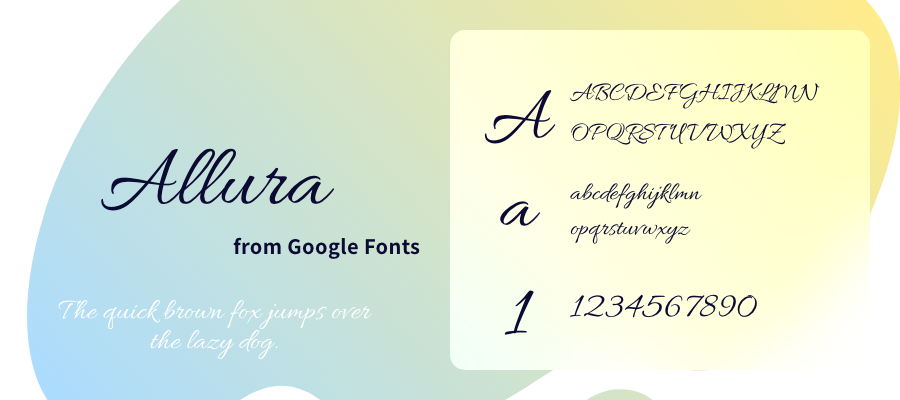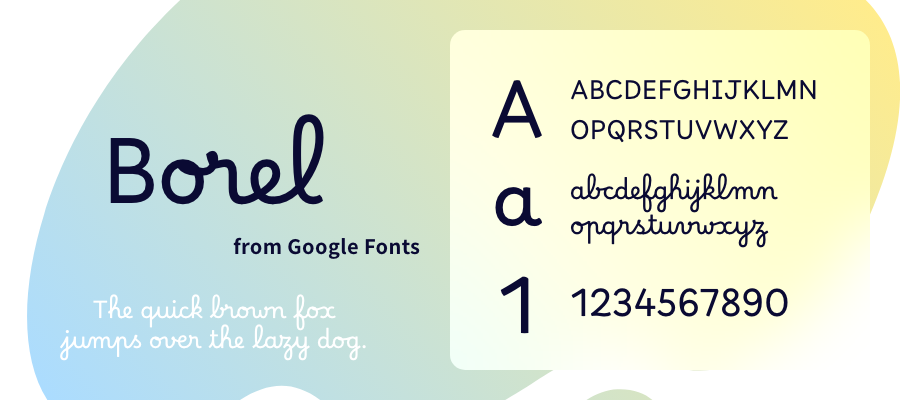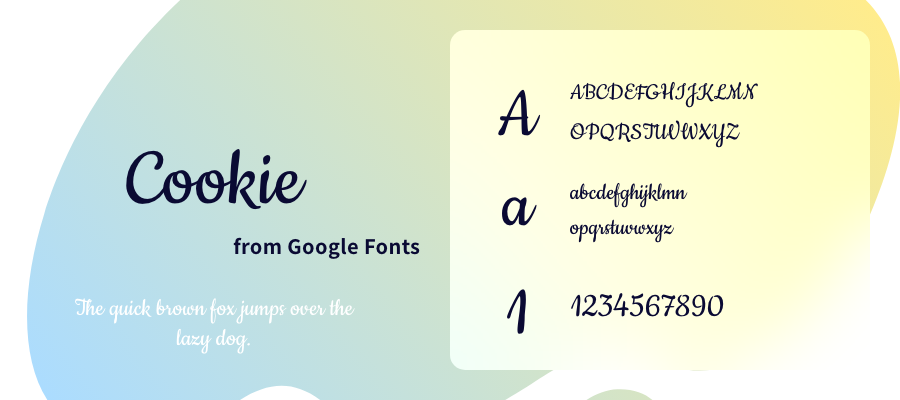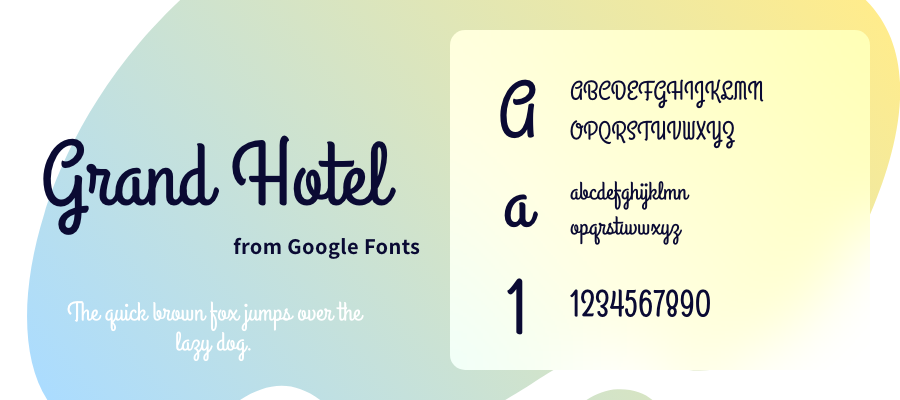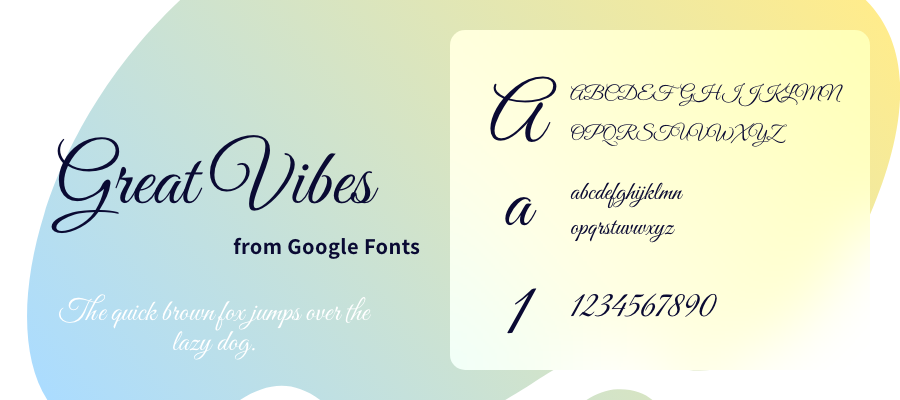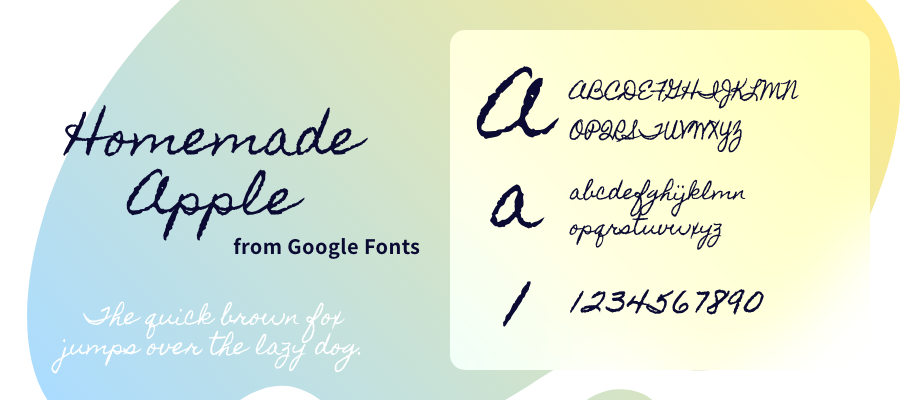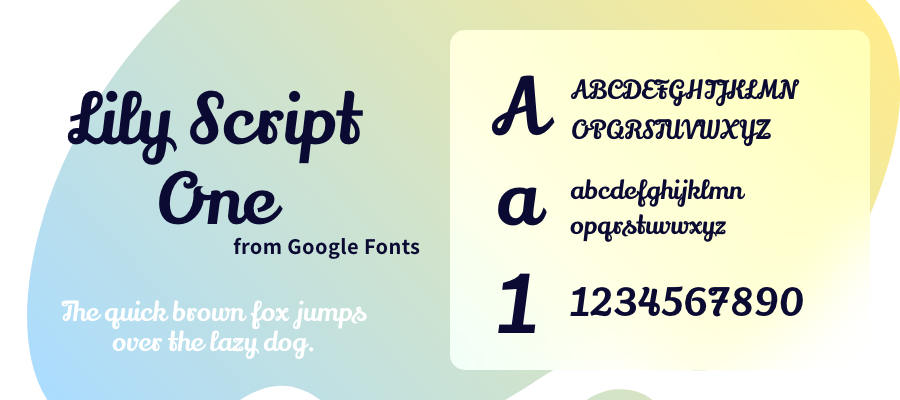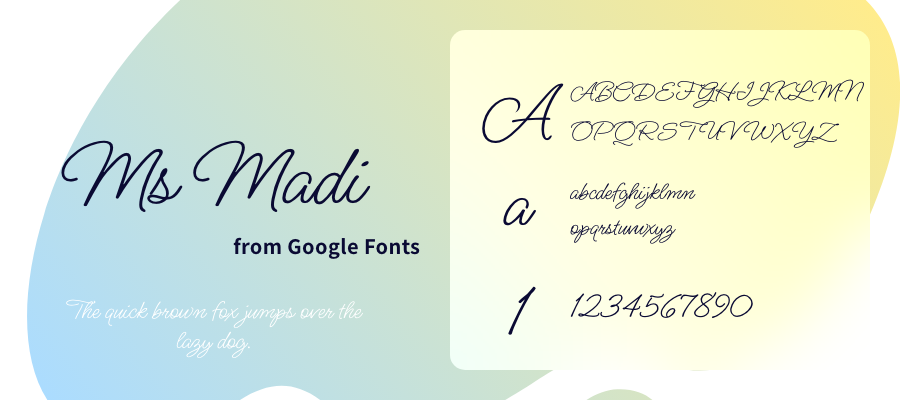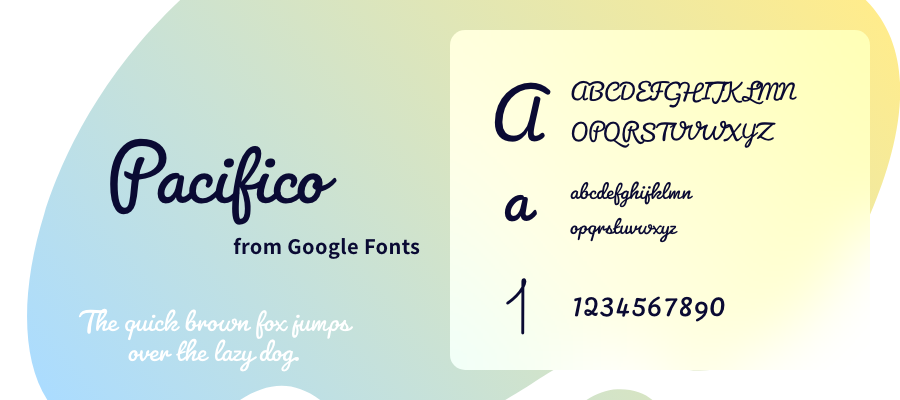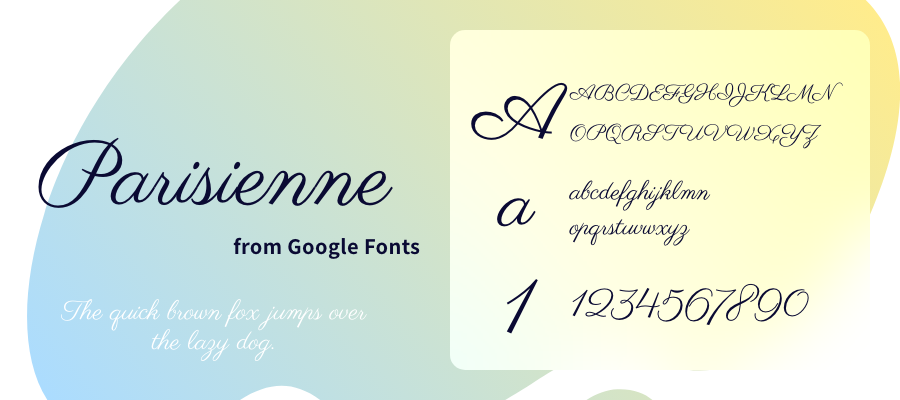
【Google Fonts】おしゃれな英字筆記体フォント15選
記念すべき第一回目は、「おしゃれな英字の筆記体フォント」。
デザインのワンポイントとしても人気の筆記体から、筆者おすすめのフォントを15個集めてみました!
おすすめの英字筆記体フォント
細め・フォーマル系
綺麗めでフォーマル感のある「Allura」
「Allura」フォントのサンプル
スッキリと高級感溢れる「Great Vibes」
「Great Vibes」フォントのサンプル
名前通りのおしゃれさ「Parisienne」
「Parisienne」フォントのサンプル
手書き感のある筆記体
筆圧のメリハリが美しい「Style Script」
「Style Script」フォントのサンプル
フォーマルながらもどこか可愛い「Rochester」
「Rochester」フォントのサンプル
コロンとしていて愛らしい「Cookie」
「Cookie」フォントのサンプル
手書き感があるのに読みやすい「Ms Madi」
「Ms Madi」フォントのサンプル
サインペンで書いたような味のある「Square Peg」
「Square Peg」フォントのサンプル
手書き感No.1!チョークで書いたような「Homemade Apple」
「Homemade Apple」フォントのサンプル
インパクトや存在感のある個性派系
とにかく可愛い♡使い所の多そうな「Sacramento」
「Sacramento」フォントのサンプル
個性的なのに読みやすい「Borel」
「Borel」フォントのサンプル
「くるん」感が魅力たっぷり「Pacifico」
「Pacifico」フォントのサンプル
ロゴとして使えばそれだけで個性溢れる「Grand Hotel」
「Grand Hotel」フォントのサンプル
文字の跳ね方が可愛く存在感のある「Lily Script One」
「Lily Script One」フォントのサンプル
存在感◎!背景に乗せてもしっかり目立ちそうな「Pattaya」
「Pattaya」フォントのサンプル